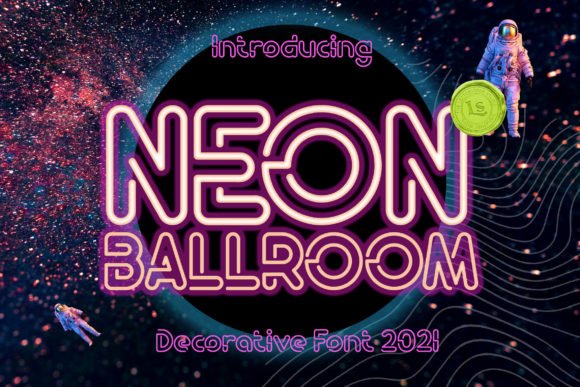
Creativefabrica Neon Ballroom Font 2021
[Creativefabrica] Neon Ballroom Font (2021)
Neon Ballroom - это ретро 3D-шрифт, который идеально впишется в любой ваш дизайн.
Повеселитесь с этим красивым шрифтом и исследуйте его бесконечные вариации.